POP的字体的基本特色是容易引人注目、容易阅读、一看便知诉求重点、具有美感、有个性、具有统一感和协调感、有效率。POP不可能无限放大。此时,如何将想要宣传的内容全部准确地表达出来就是个问题。虽然传达给用户的信息越详细越好,但是如果将很多的内容用很小的字写在POP上,如果顾客看不清,索性根本不去看,所以一定要选择字形方正大方的字体,才能展示海报要传递的信息。
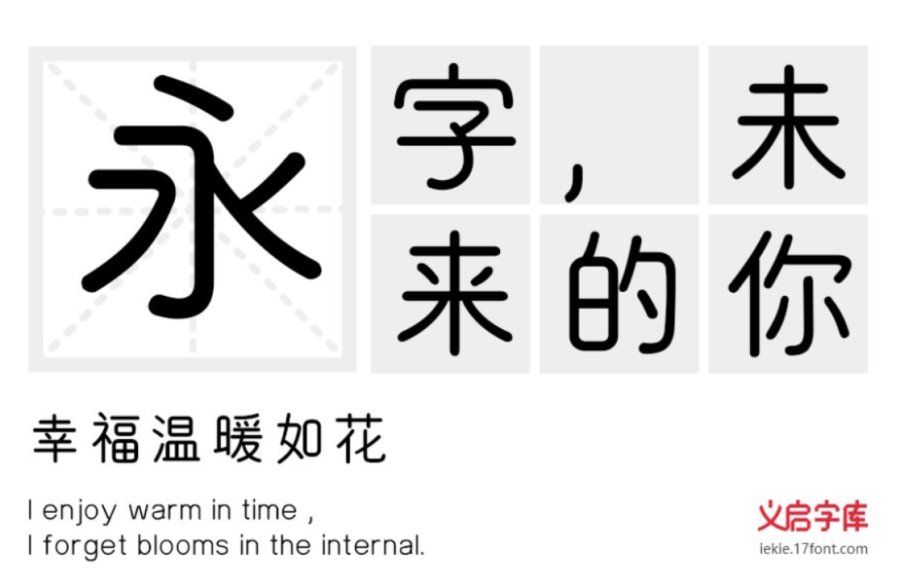
上面这款图片字体叫做“晚安喵”。笔画遵循“上大下小,横不平,竖不直,口写大,内大外小,左窄右宽,重心偏下”的原则。线条顺滑、一气呵成。字形清晰转折流畅,饱和、平稳而不失美感,简洁有力。可以把重要的价值清晰地表达出来。
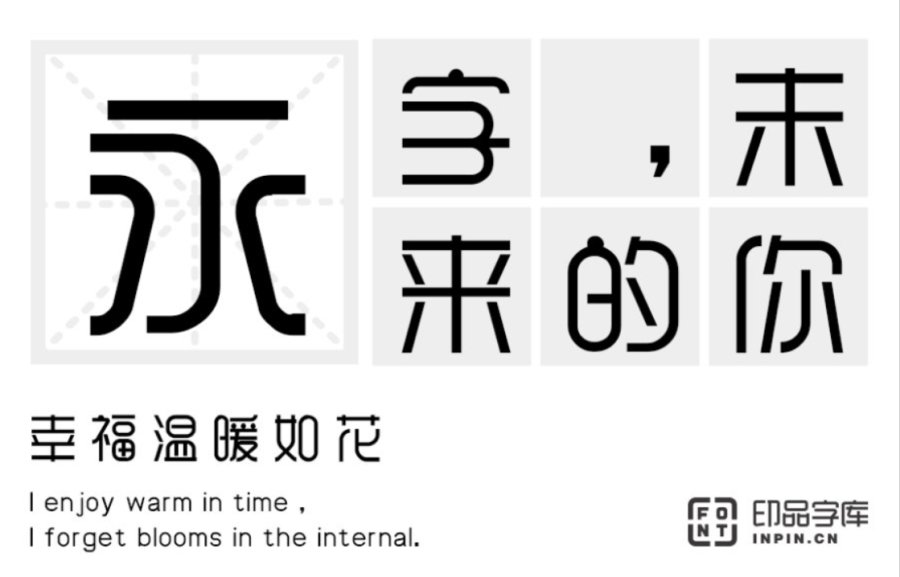
这款“印品雅圆体”对弧形做了内凹外凸的处理,使得笔画更加居中圆滑。表面结构匀称统一,字型做了细致比例的调整,整体观来更加珠圆玉润。加强装饰感的同时,多添了一分俏皮可爱。